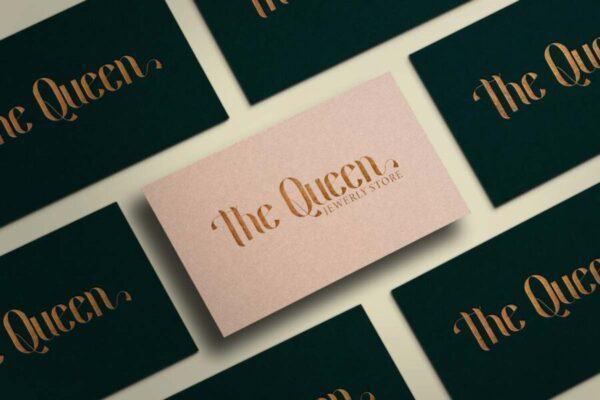
GenZ giới thiệu bạn bộ font Hardenburg, đây là phông chữ hiển thị sans serif lấy cảm hứng từ phong cách Gothic và Trung cổ. Phông chữ đi kèm với ba tùy chọn kiểu: Thông thường, Nghiêng và In đậm. Nó có phong cách tuyệt đẹp, bí ẩn, phong cách, cổ điển và cổ điển. Phông chữ Hardenburg sẽ hoàn hảo cho việc xây dựng thương hiệu, quảng cáo, khuyến mãi, tiêu đề, v.v. Nó rất thanh lịch, sang trọng, phong cách và độc đáo.